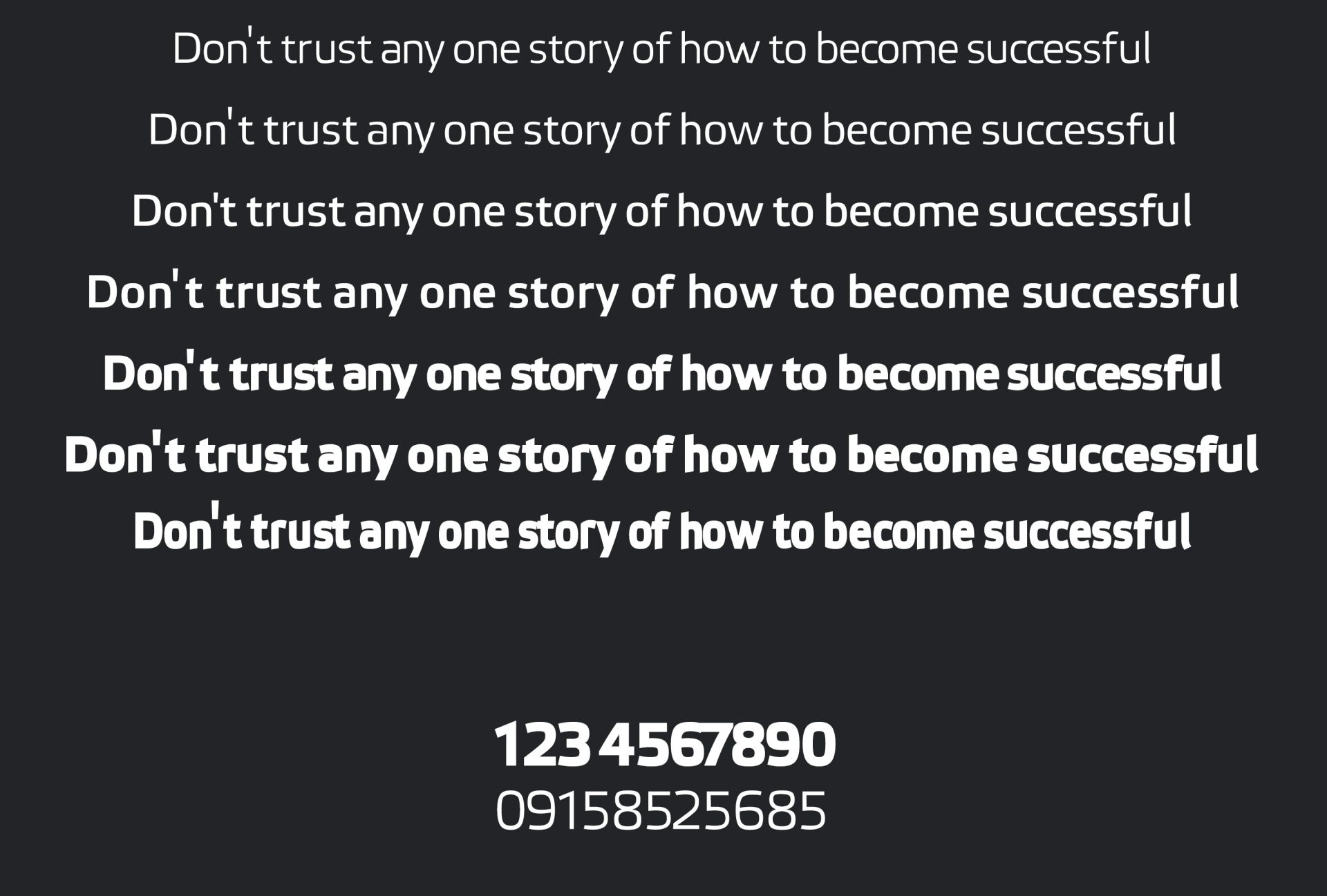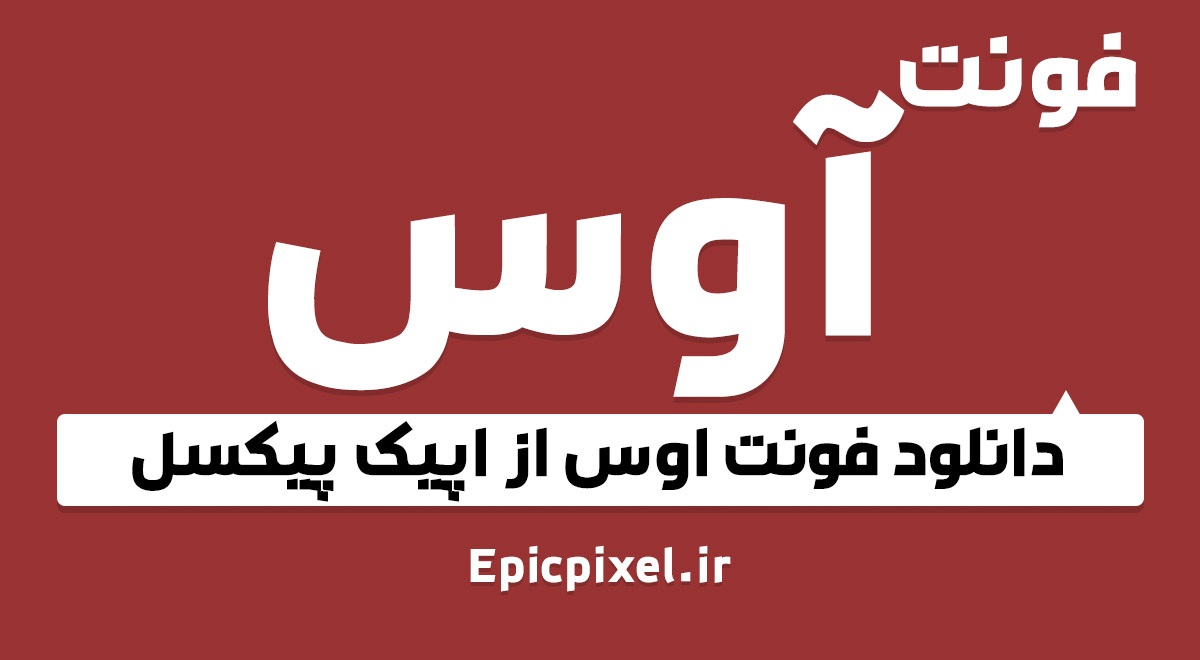
7 فونت آوس فارسی
دانلود مجموعه کامل فونت AWS فارسی Font آوس پرو |
| ⭐ توضیحات | نسخه شبیه سازی شده آوس پرو پشتیبانی از حروف فارسی و انگلیسی اعداد فارسی Fu Num و انگلیسی بهمراه نسخه وب |
فونت آوس AWS Pro زیبایی، ظرافت و تنوع در صنعت گرافیک
در دنیای گرافیک، فونت ها نقشی اساسی ایفا می کنند. آنها پیام های ما را به مخاطب انتقال می دهند و تأثیر زیادی بر درک و احساسات آنها می گذارند. یکی از فونت های محبوب و پرکاربرد در صنعت گرافیک، فونت آوس AWS Pro می باشد. این فونت با طراحی ظریف و زیبایی خود، حس زیبایی و ظرافت را به مخاطب منتقل می کند. در این مقاله به بررسی ویژگی های فونت آوس، کاربردهای آن و نحوه انتخاب فونت مناسب برای پروژه های خود خواهیم پرداخت.
ویژگی های فونت آوس AWS Pro
فونت آوس AWS یک فونت Sans Serif است که دارای خطوط نازک و منحنی های ظریف می باشد. این فونت به خوبی با سبک های طراحی مینیمالیستی و مدرن هماهنگ است. فونت اوس در چند وزن موجود است که به شما امکان می دهد تا پیام خود را با شدت های مختلف بیان کنید. همچنین، این فونت شامل کاراکترهای فارسی نیز می باشد که آن را برای استفاده در پروژه های فارسی مناسب می کند.
کاربردهای فونت آوس
فونت آوس AWS برای طیف گسترده ای از پروژه های گرافیکی قابل استفاده است. برخی از کاربردهای اصلی این فونت عبارتند از:
طراحی لوگوها و تایپوگرافی
طراحی بنرها و پوسترها
طراحی وب سایت ها و صفحات فرود
طراحی کارت های دعوت و تبریک
طراحی بسته بندی محصولات غذایی و نوشیدنی
طراحی صفحات مجله
طراحی تبلیغات در فضای مجازی
طراحی عناوین کتاب و مقالات
هنگام انتخاب فونت برای پروژه خود، عوامل مختلفی را باید در نظر بگیرید، از جمله سبک طراحی پروژه، پیامی که می خواهید منتقل کنید و مخاطبان هدف خود. فونت آوس برای پروژه هایی که نیاز به حس زیبایی و ظرافت دارند، مانند طراحی لوگو شرکت های هنری یا طراحی صفحات مجله، بسیار مناسب است.
سوالات درباره فونت آوس
سوال: آیا فونت آوس فارسی پشتیبانی می کند؟
بله، فونت آوس شامل کاراکترهای فارسی نیز می باشد.
سوال: آیا فونت آوس AWS Pro برای طراحی صفحات وب مناسب است؟
بله، فونت آوس برای طراحی صفحات وب بسیار مناسب است، زیرا خوانا و سبک است.
سوال: آیا فونت آوس AWS Pro برای طراحی گرافیک چاپی مناسب است؟
بله، فونت آوس AWS Pro برای طراحی گرافیک چاپی نیز مناسب است، زیرا کیفیت بالایی دارد.
فونت آوس AWS Pro یک فونت زیبا و کاربردی است که در پروژه های مختلف گرافیکی کاربرد دارد. این فونت به دلیل طراحی ظریف و زیبایی خود، حس زیبایی و ظرافت را به مخاطب منتقل می کند و برای پروژه هایی که نیاز به این حس دارند، بسیار مناسب است. همچنین، این فونت رایگان و شامل کاراکترهای فارسی نیز می باشد.